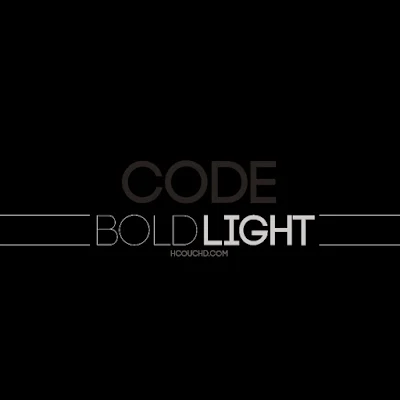
خط Code خط جميل ، حيت أنه بسيط ، و سبق أن استعملناه في درس ” درس 137 : كيفية إنشاء تأثير النص لأوراق الخريف في فوتوشوب + ملف PSD ” ، يمكنك تحميل هذا خط من رابط أسفله …